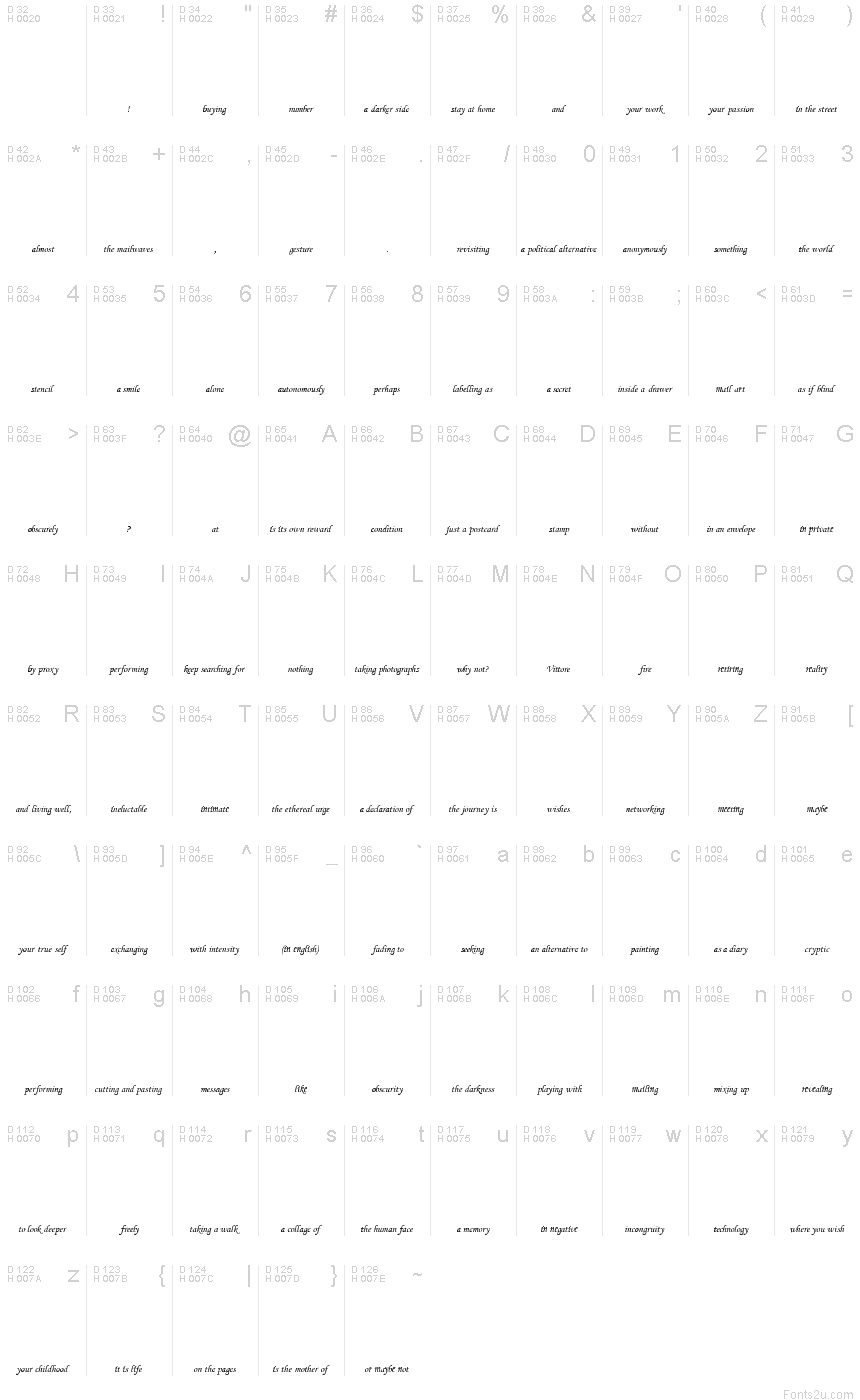
Obscure Actions, stworzony przez Keitha Batesa dla OA04 przy użyciu Corsivy wybranej przez Vittore Baroniego, to darmowy krój kaligraficzny. Jego cienkie, pochylone pociągnięcia i połączone litery przypominają szybkie, formalne pismo odręczne, z długimi łukami, które utrzymują linię w ruchu.
Ten krój sprawdza się dobrze w materiałach wystawienniczych, okładkach tomików poetyckich, zaproszeniach i osobistej papeterii, które wymagają intymnego, odręcznego głosu. Jego delikatna konstrukcja najlepiej prezentuje się z odrobiną przestrzeni, zwłaszcza na fakturowanych tłach lub w układach z gęstymi grafikami.
Created by Keith Bates for OA04: a year of Obscure Actions, using Vittore Baroni's choice of typeface, Corsiva.